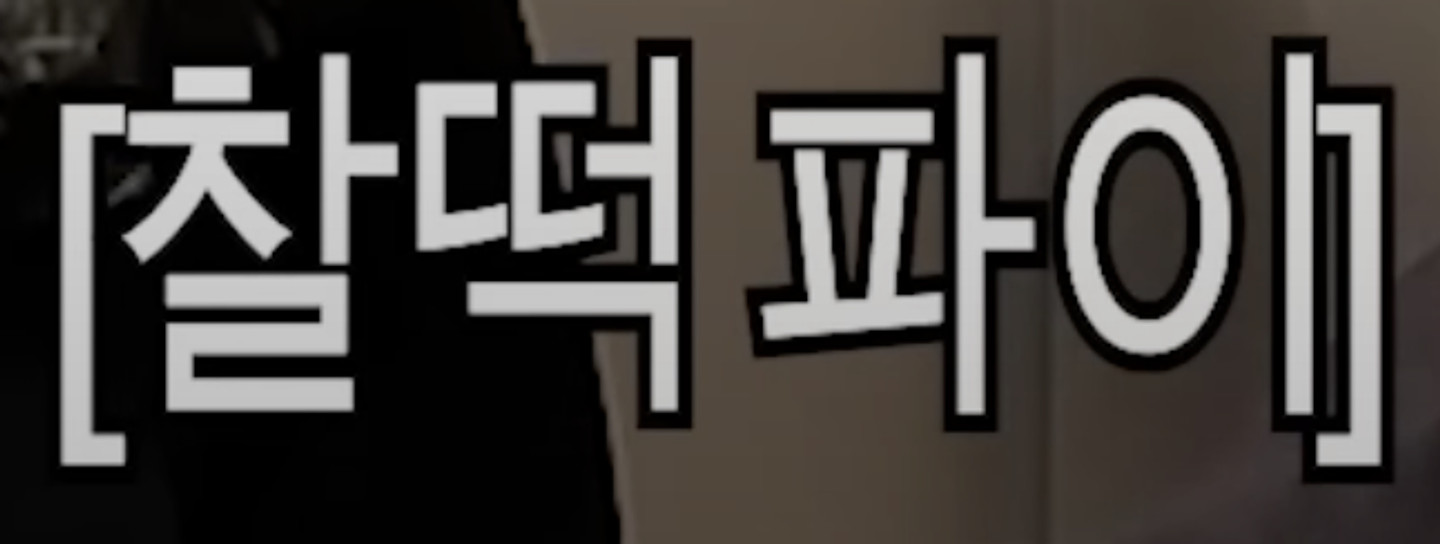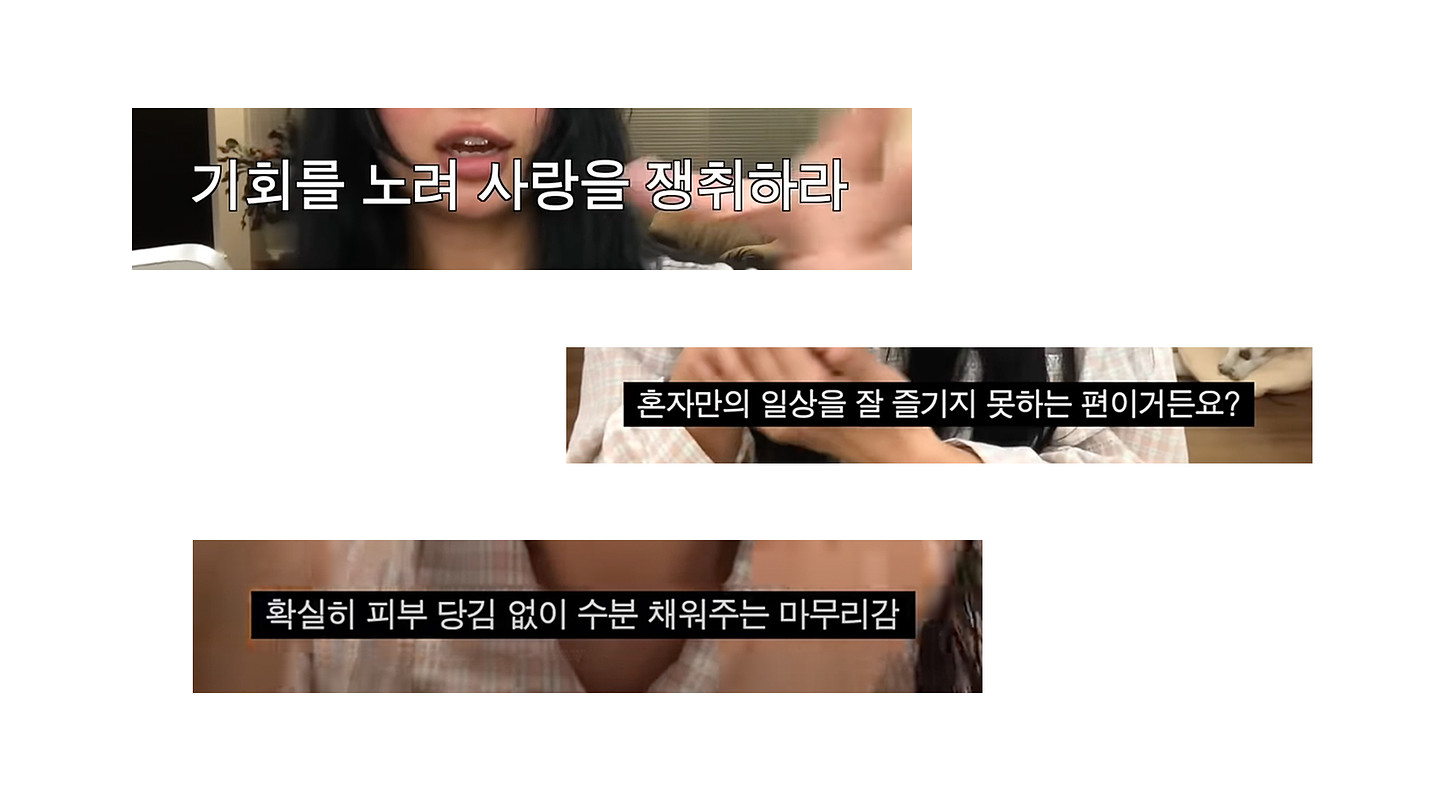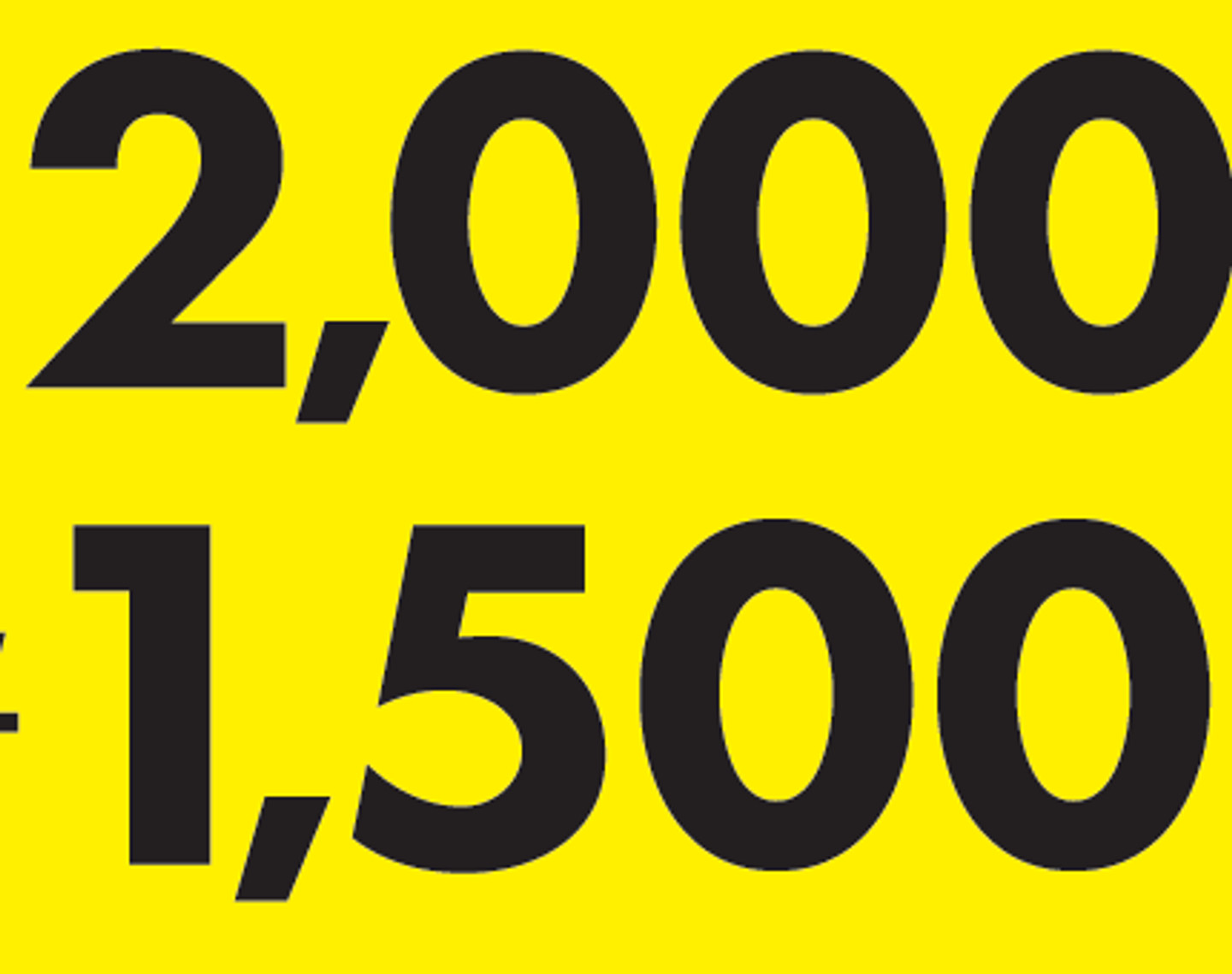
이 폰트 너무 궁금해요. 굴림인가.. 네모꼴로 되어있는데, ㅅ 과 ㅈ, ㅊ의 획 특징과 ㄷ,ㅍ,ㄹ 의 속공간 폭이 좁다는 게 특징인듯 하네요.. 아무리 다 뒤져봐도 안 나오는데,, 혹시 아시는 분?
O랑 G가 큰 폰트인데 도저히 못찾겠습니다 ㅠㅠ 영어에 쓰인 폰트가 뭔지 찾고 있습니다. 제발 도와주세요 ㅠㅠ https://www.artic.or.kr/base/board/read?boardManagementNo=1&boardNo=3871&searchCategory=&page=1&searchType=total&searchWord=%EB%9D%BC%EC%9D%B8%EC%97%85&menuLevel=3&menuNo=48 해당 링크에 볼드체로 쓰인 영어랑 숫자 폰트입니다 ㅠㅠ
재구언 님의 동영상 중 일부입니다. 한글은 프리텐다드 느낌이고, 숫자는 Gothic A1인 거 같은데 위 처럼 2개 합쳐진 느낌의 폰트는 없을까요?